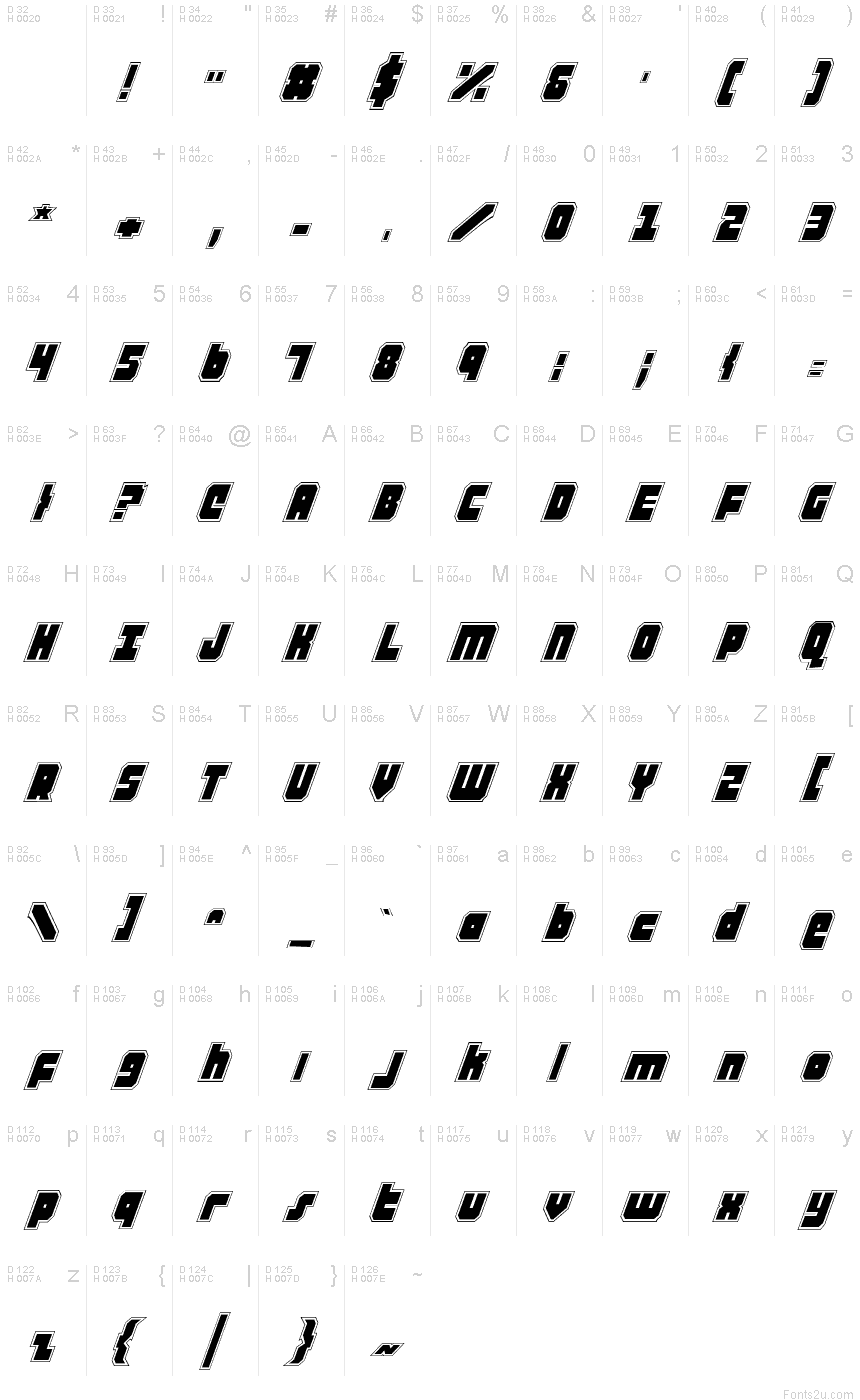
Alpha Taurus Pro Italic od Iconian Fonts to darmowy techniczny krój pisma typu display o wyrazistym, futurystycznym charakterze sci-fi. Litery są uformowane w masywne, kanciaste bloki i otoczone warstwowymi obrysami, co nadaje słowom mechaniczny, pancerny wygląd, nie tracąc przy tym komiksowej energii.
Świetnie sprawdzi się w logotypach gier, ulotkach arcade, nagłówkach plakatów, okładkach albumów i planszach tytułowych, wszędzie tam, gdzie potrzebujesz dynamiki i nieco drapieżnego wyglądu. Jako darmowy font, doskonale nadaje się także do krótkich projektów brandingowych, grafik e-sportowych i tytułów, ponieważ pogrubione, warstwowe obrysy dodają wyrazistości nawet krótkim słowom.